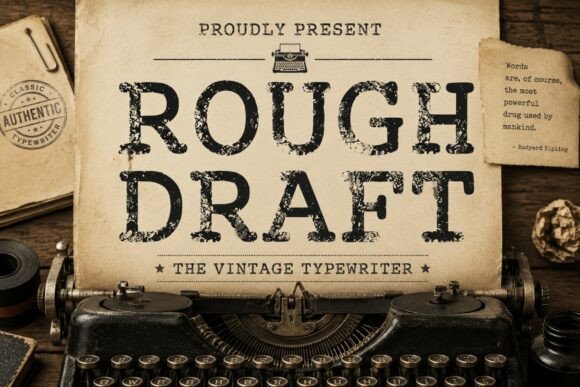
Rough Draft
Rough Draftのような高品質の素材をお探しの場合、このプレミアムパッケージはクリエイティブなプロジェクトに素晴らしい選択です。
POD(オンデマンド印刷)製品、結婚式の招待状、またはソーシャルメディアのグラフィックを作成している場合でも、Rough Draftは理想的です。